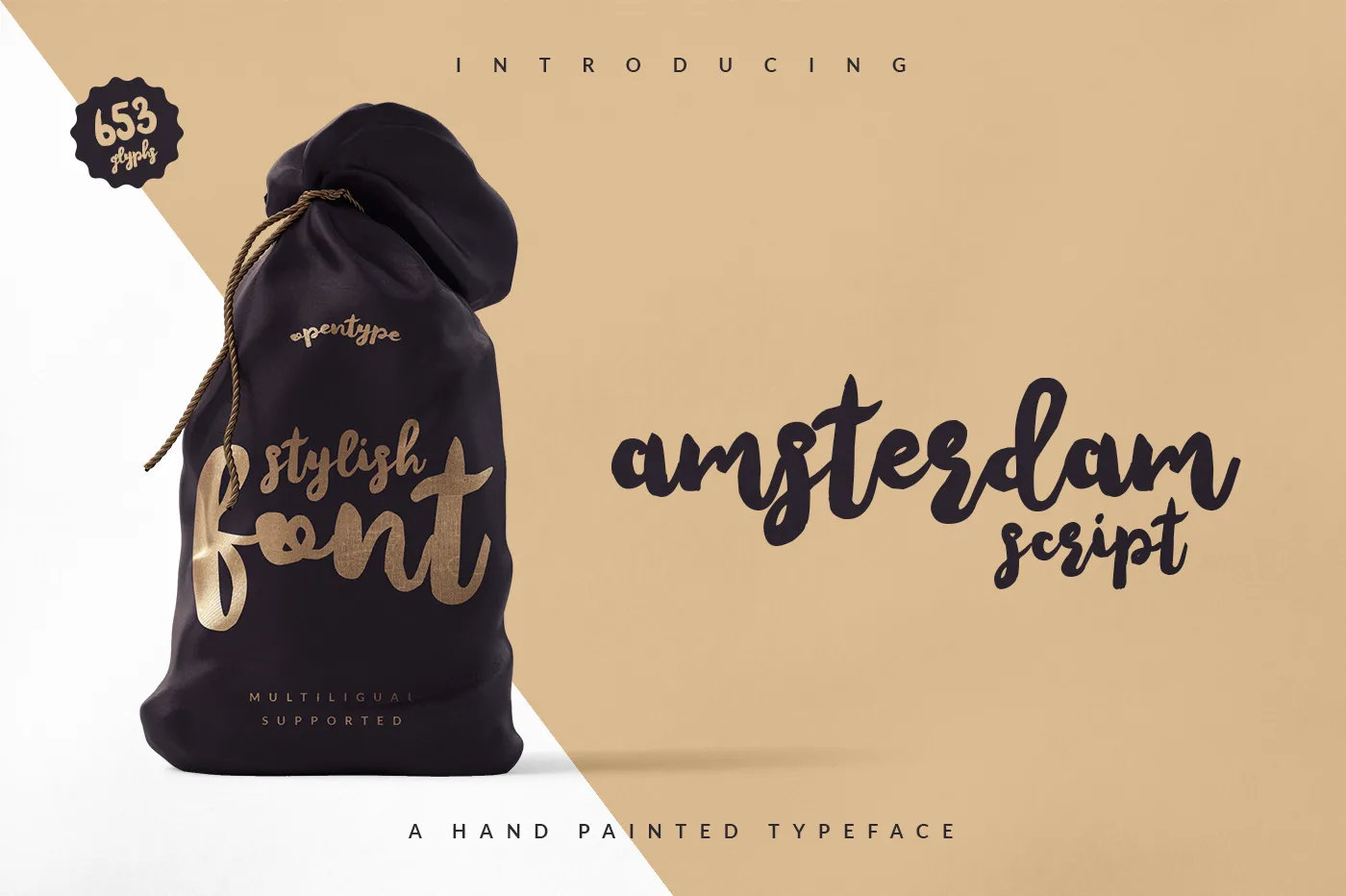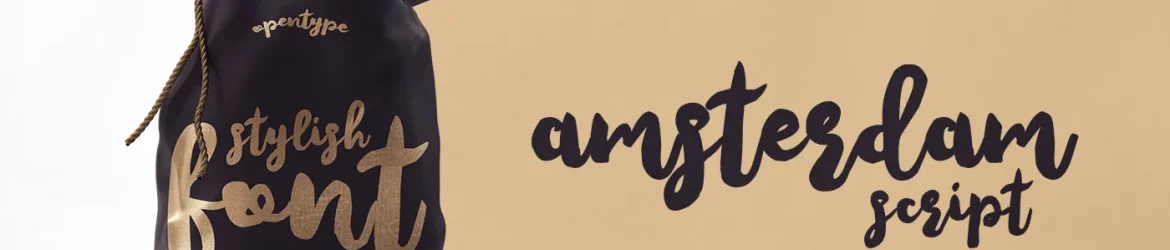
Amsterdam Script Font – Download Grátis
Introduzimos Amsterdam Script Font! Esta é uma fonte criada à mão através do uso de um pincel grosso, designada por Amsterdam e compartilhada pelo site de arte de fontes font art . Ela se destaca pela sua delicadeza e facilidade em ser usada para diversas finalidades, como estampas de camisetas, bolsas e convites. A Amsterdam Script ganha mais atração ainda com seus caracteres que ganham “swashes”, ou seja, extensões nas bordas dos caracteres. Estamos muito felizes por você ter descoberto nossa fonte. Esperamos que você goste do Amsterdam Script!